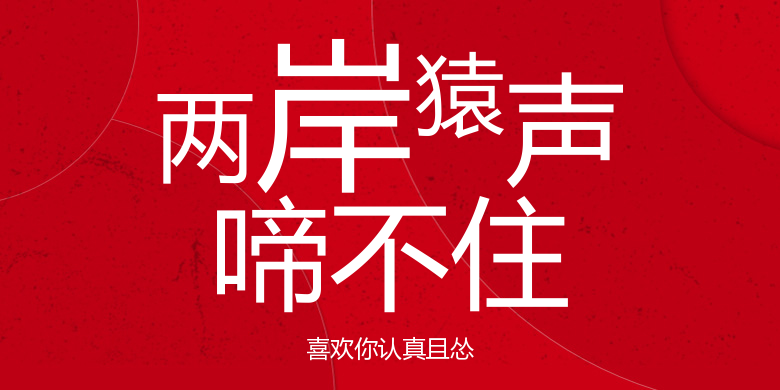
喜欢你认真且怂
喜欢你认真且怂,这款字体结构工整、笔画清晰,兼顾美观与易读性,适用于标题、正文、海报、包装、LOGO 等多种场景。字形优雅稳定,风格百搭耐看,适配日常排版与创意设计,让文字呈现更舒适、更具质感。喜欢你认真且怂一笔一画,皆是细节,以均衡的比例、流畅的线条打造舒适视觉体验,字形端正大气,风格简约现代。无论是商业设计、品牌宣传还是日常排版,都能轻松驾驭,让文字更有格调与力量。喜欢你认真且怂字体下载。